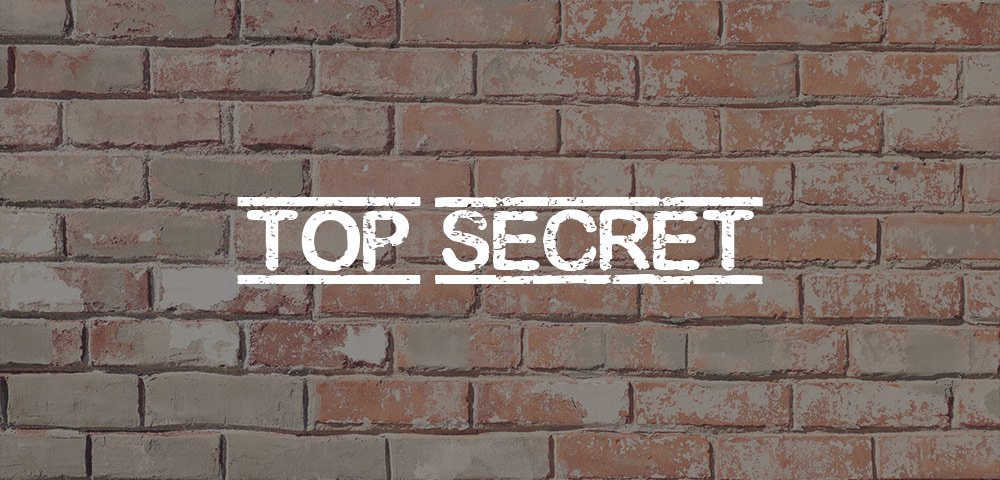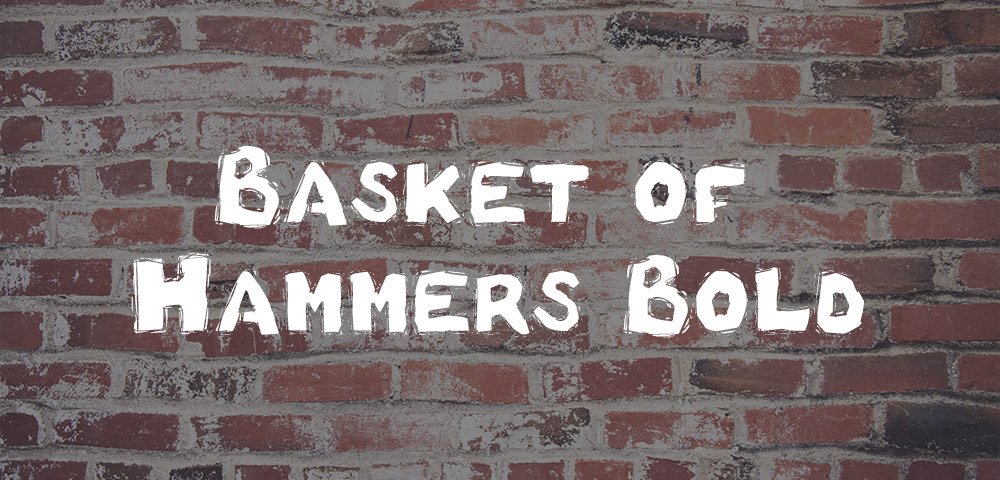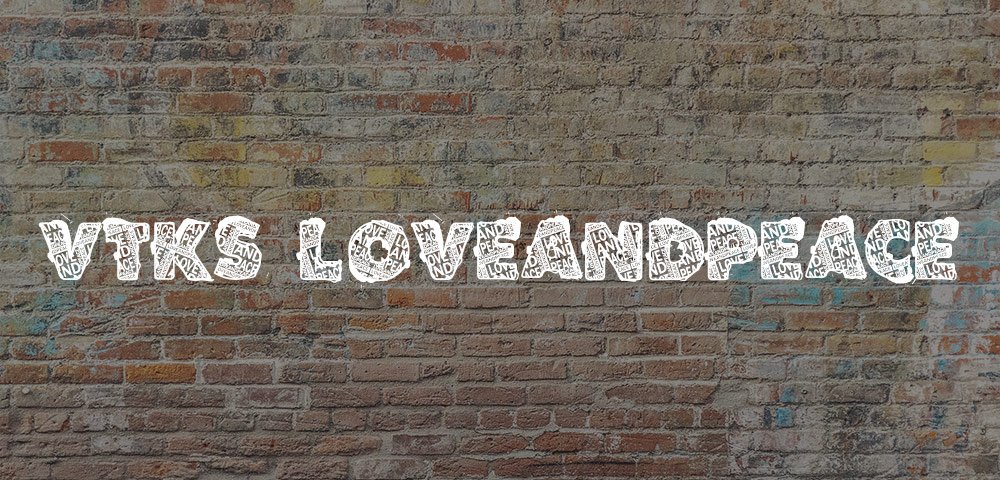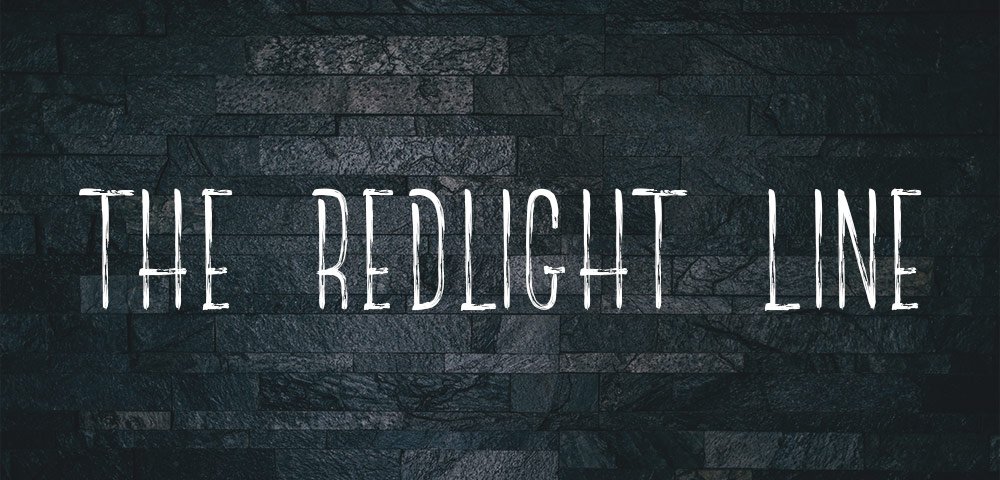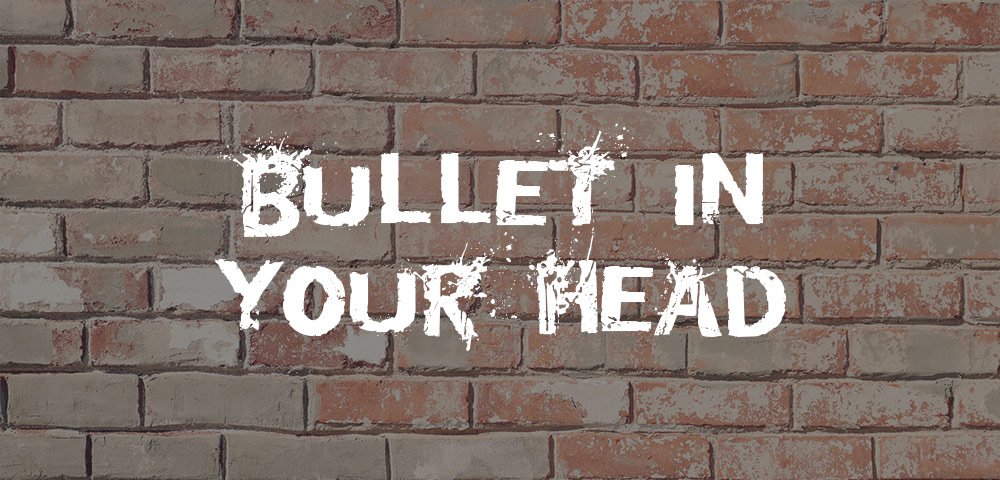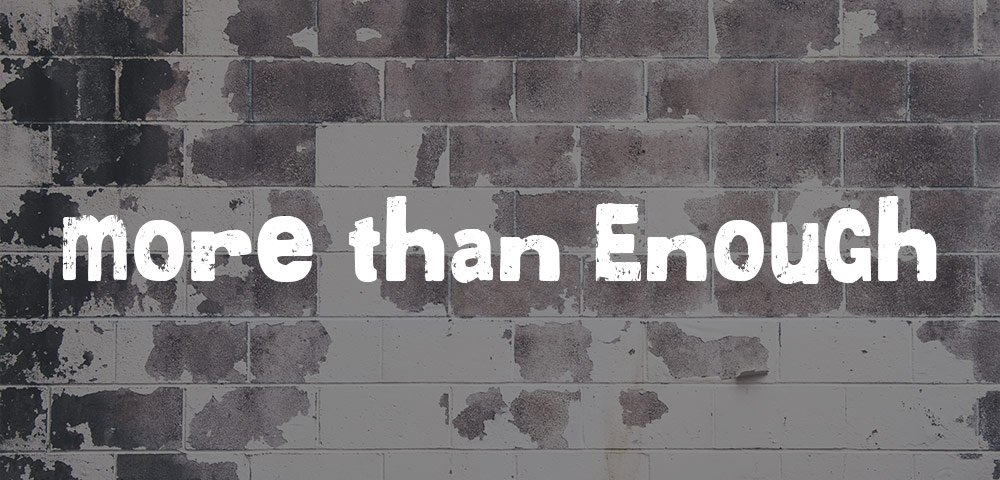
30 fontes gratuitas no estilo Grunge
O termo “grunge”, que significa literalmente “sujeira” ou “imundice”, ficou conhecido especialmente como um gênero de rock que surgiu na década de 80, com raízes no punk e no heavy metal.
O estilo ficou tão conhecido que até hoje seu modo de se vestir ou de pentear o cabelo é copiado por muitas pessoas. É claro que não poderia ser diferente com estilos de fontes.
Sendo assim, separamos 30 fontes gratuitas que remetem a esse estilo para que você possa utilizar em seus projetos.
Refurbished
Ghost Reverie
AA Typewriter
The Sickmen
Grunge
Scorched Earth
White on Black
Top Secret
Cut The Crap
Fail
Oh God Why
Dharma Punk
Personal Services
Buy More
Action of the Time
DCC The aliens are coming
Night Stalker
Acid Label
Dock 51
Ambulance Shotgun
Basket of Hammers Bold
Heroin 07
VTKS LOVEANDPEACE
Alcatraz
Distort you a Lesson
District
Reclaim
The Redlight Line
Bullet in Your Head
More Than Enough